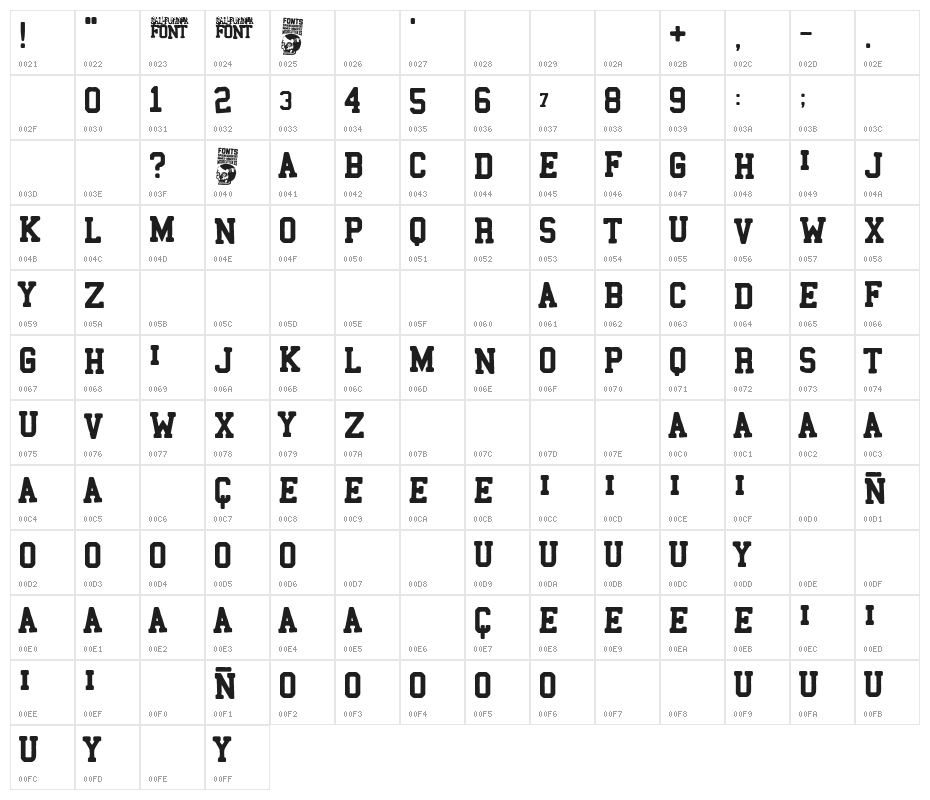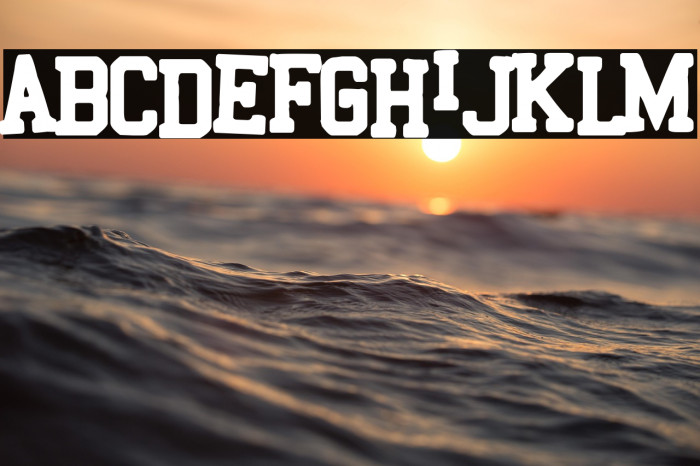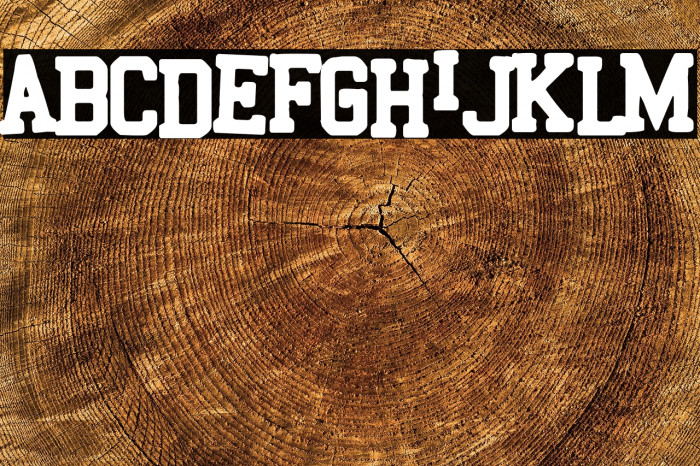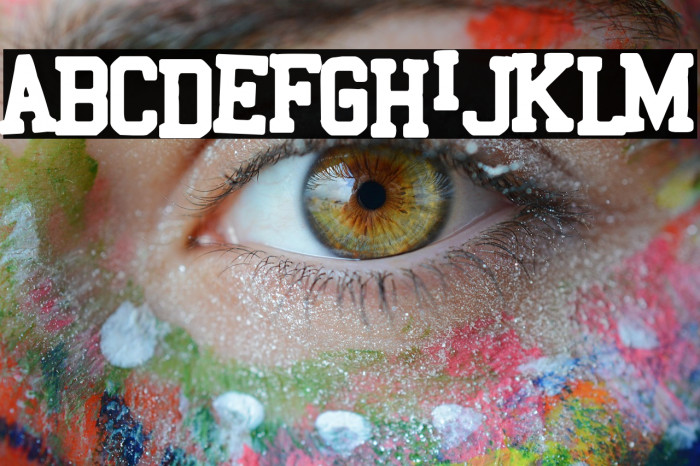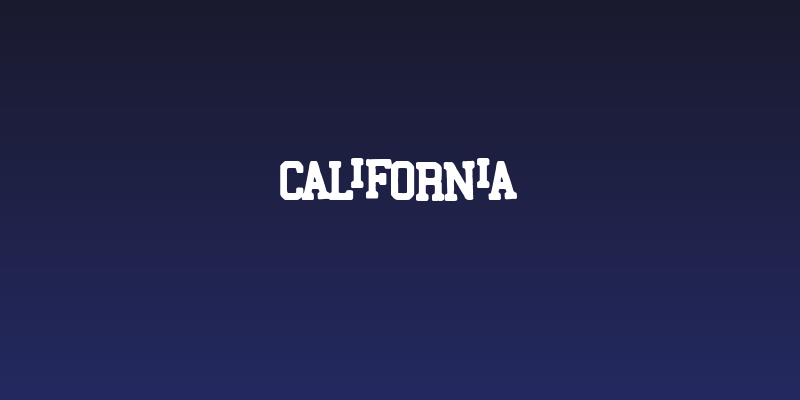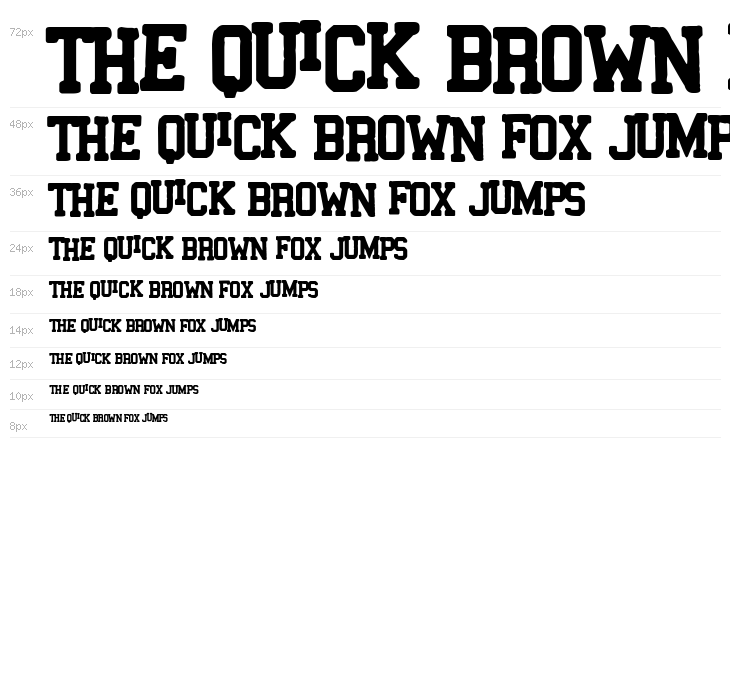
California Font
✎ Western
| Categorías | Western |
| Estilo general | Vintage |
| Caso de uso | Headlines, Posters, Branding |
| Proyectos propuestos | Perfect for posters, branding, headlines, and any design needing a strong, vintage aesthetic. |